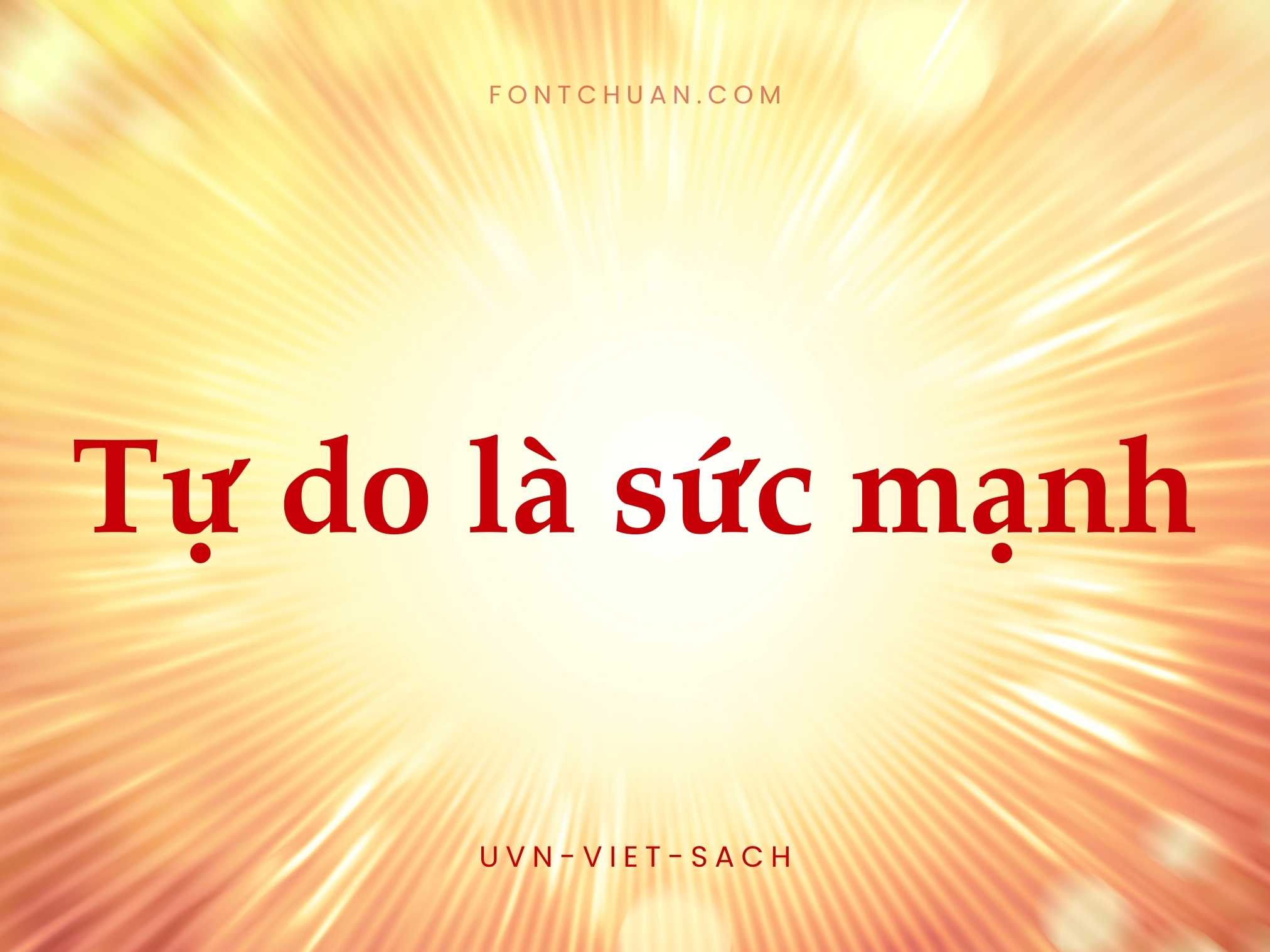
Font UVN Viet Sach Việt Hóa
UVN Việt Sách là một phông chữ serif được thiết kế bởi Tom Truong vào năm 2001. Phông chữ này có các đường nét rõ ràng và tinh tế, tạo nên sự trang nhã và dễ đọc. UVN Việt Sách hỗ trợ đầy đủ các ký tự tiếng Việt, giúp người dùng dễ dàng sử dụng trong các dự án liên quan đến ngôn ngữ Việt Nam.
Với thiết kế rõ ràng, trang trọng và dễ tiếp cận, UVN Việt Sách không chỉ phù hợp cho tiêu đề, văn bản dài, thiết kế logo hay các ấn phẩm in ấn mà còn là một Font chữ giáo dục lý tưởng. Phông chữ này đặc biệt thích hợp cho sách giáo khoa, tài liệu học tập, bài giảng và các ấn phẩm đào tạo, giúp nâng cao trải nghiệm học tập và truyền đạt thông tin một cách chuyên nghiệp và dễ hiểu.